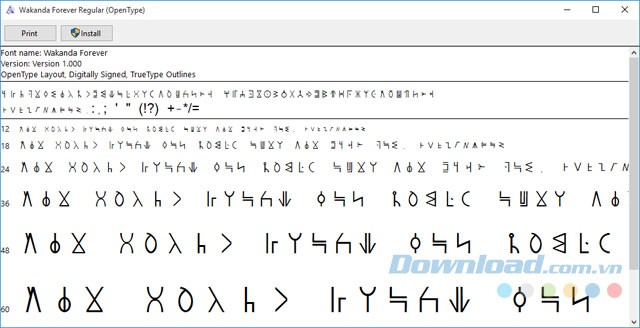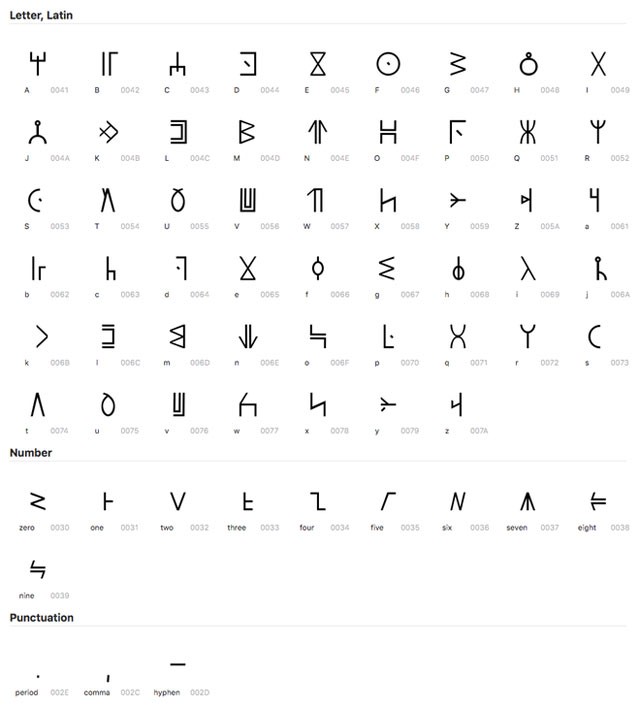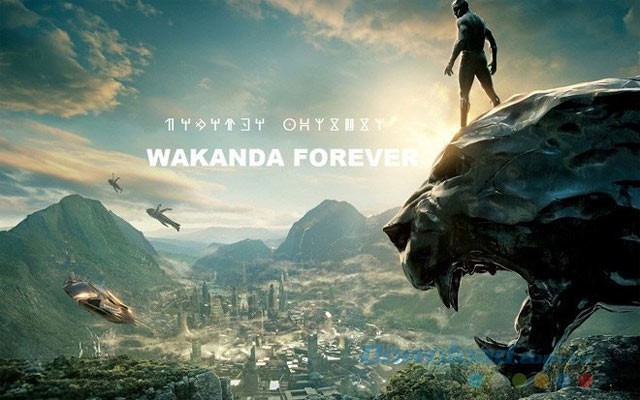
Font Wakanda Forever 1.0: Font chữ Black Panther tuyệt đẹp
Khám phá Bộ Font Wakanda Forever: Nguồn Cảm Hứng Từ Ngôn Ngữ Wakanda
Bộ font Wakanda Forever được thiết kế dựa trên hệ thống chữ viết Wakanda độc đáo, mang đậm tính biểu tượng và xuất hiện ấn tượng trong bộ phim Black Panther (Chiến binh báo đen). Bộ font này sẽ giúp bạn dễ dàng tạo ra các thiết kế đồ họa, đặc biệt là poster, với những ký tự cổ đại đầy mới lạ.
Bộ font Wakanda Forever
Tận hưởng sự sáng tạo không giới hạn với bộ font Wakanda Forever.
Ý tưởng về bộ font chữ này bắt nguồn từ những hình ảnh về bảng chữ cái Wakanda được thấy trong phim. Adam Shady, một nhà thiết kế tài năng và thành viên tích cực của Dribbble – nền tảng trực tuyến nổi tiếng dành cho cộng đồng designer toàn cầu – đã bắt đầu quá trình chuyển đổi chúng thành một bộ font hoàn chỉnh, mở ra cơ hội sáng tạo cho mọi người.
Bảng chữ cái Wakanda Forever
Bảng chữ cái Wakanda và sự tương ứng với các ký tự Latin do Adam Shady thiết kế.
Khám phá những điểm nổi bật của bộ font Wakanda Forever
• Bộ font Wakanda Forever sở hữu vẻ đẹp độc đáo, với các đường nét tượng hình ấn tượng.
• Kiểu chữ tinh tế này đặc biệt phù hợp cho các dự án thiết kế như bìa sách, áp phích quảng cáo.
• Bộ font hoàn chỉnh bao gồm đầy đủ các ký tự, con số và dấu câu cần thiết.
Thiết kế
Hình ảnh minh họa kết quả khi sử dụng với phần mềm MS Paint.
Dành cho những ai đam mê bộ phim Black Panther đầy ăn khách, việc tải và trải nghiệm font chữ Wakanda Forever sẽ mang đến cơ hội khám phá ngôn ngữ đặc trưng của bộ tộc siêu anh hùng này.
Font chữ này không chỉ là công cụ thiết kế, mà còn là cách để bạn thể hiện sự yêu thích đối với văn hóa và thế giới quan trong phim.